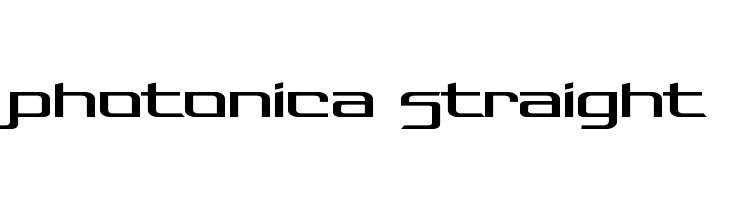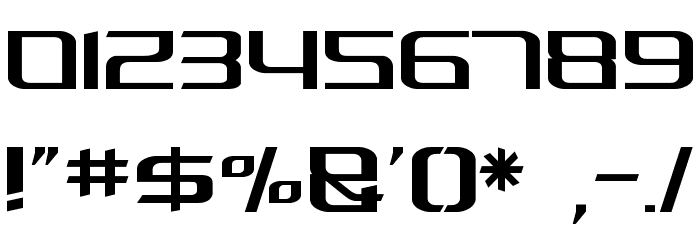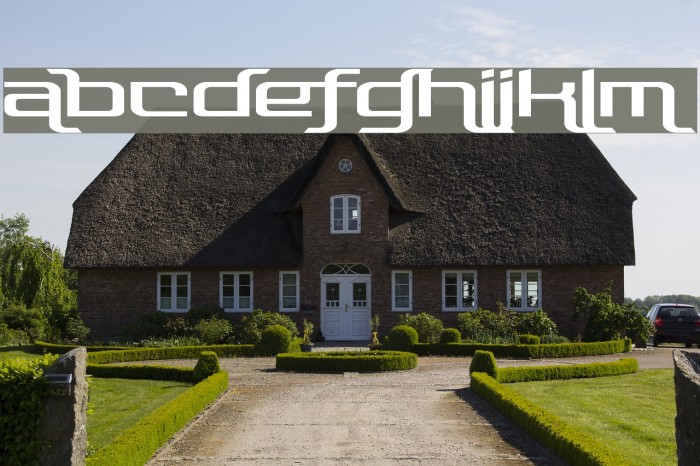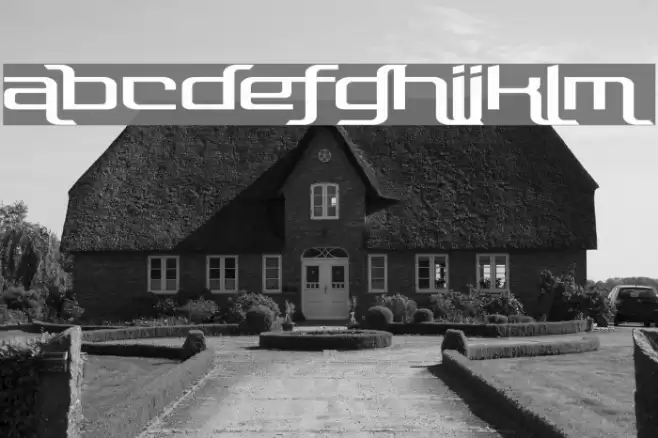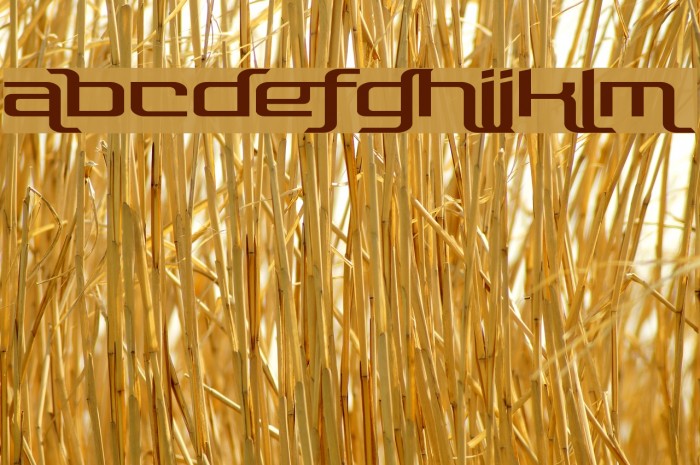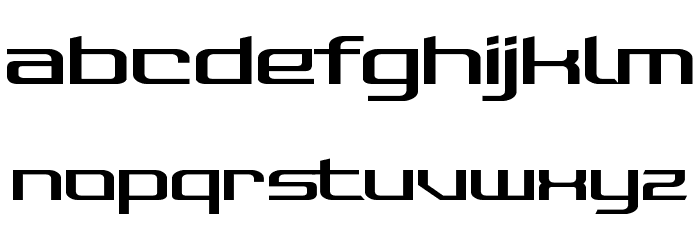
Photonica Straight Font
| Gesamtstil | Futuristic |
| Anwendungsfall | Logos, Headlines, Digital interfaces |
| Vorgeschlagene Projekte | Ideal for tech-related branding, sci-fi book covers, digital interfaces, and modern advertising campaigns. |